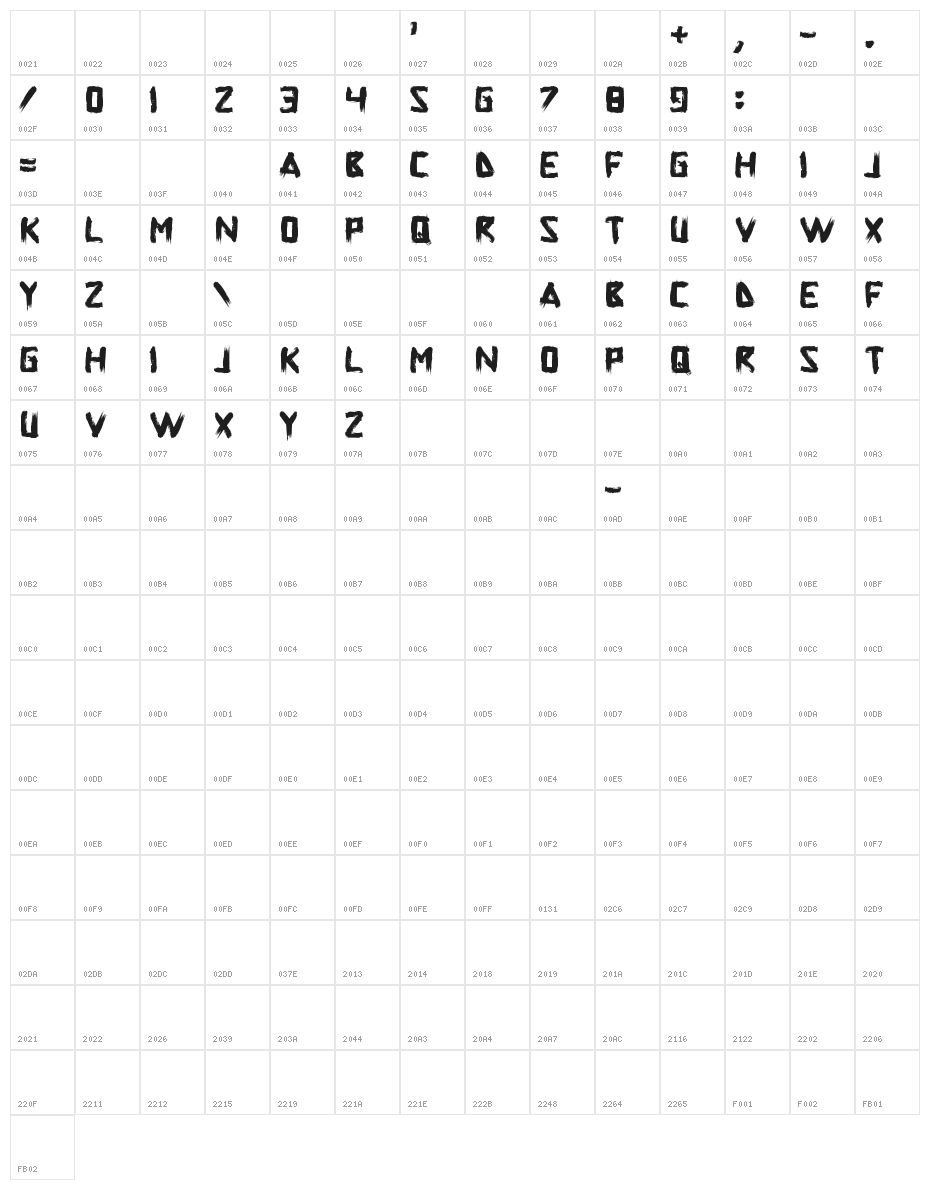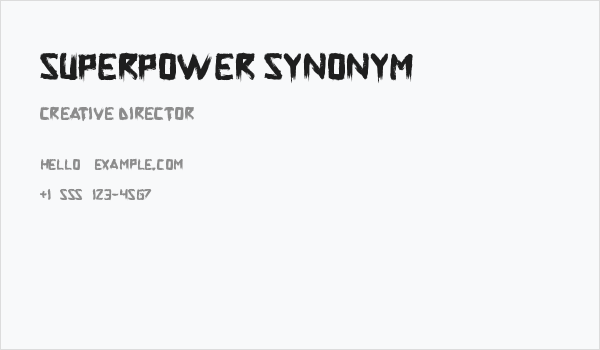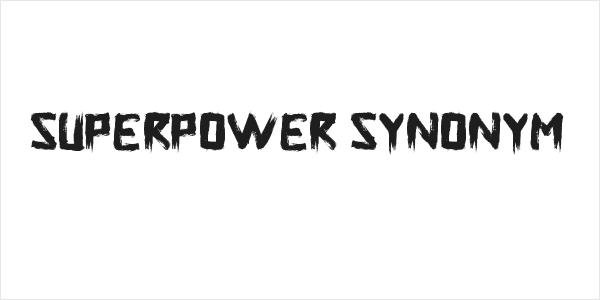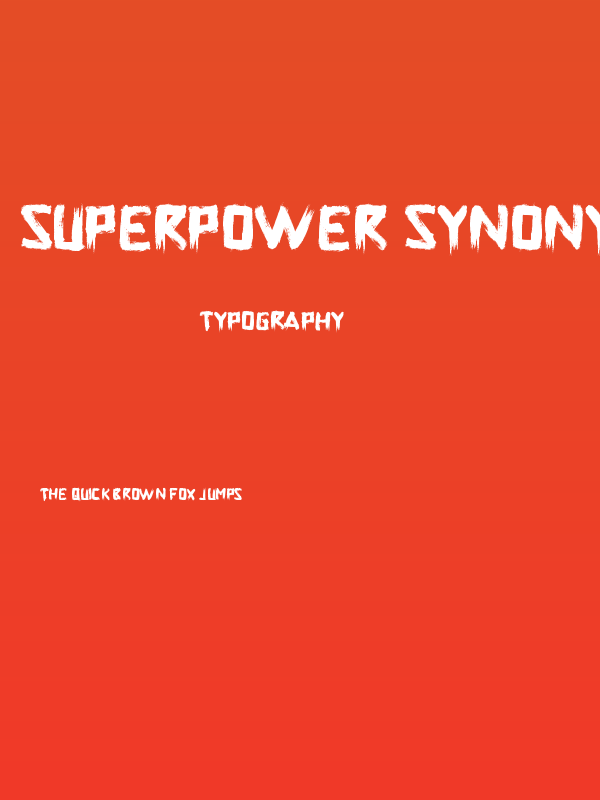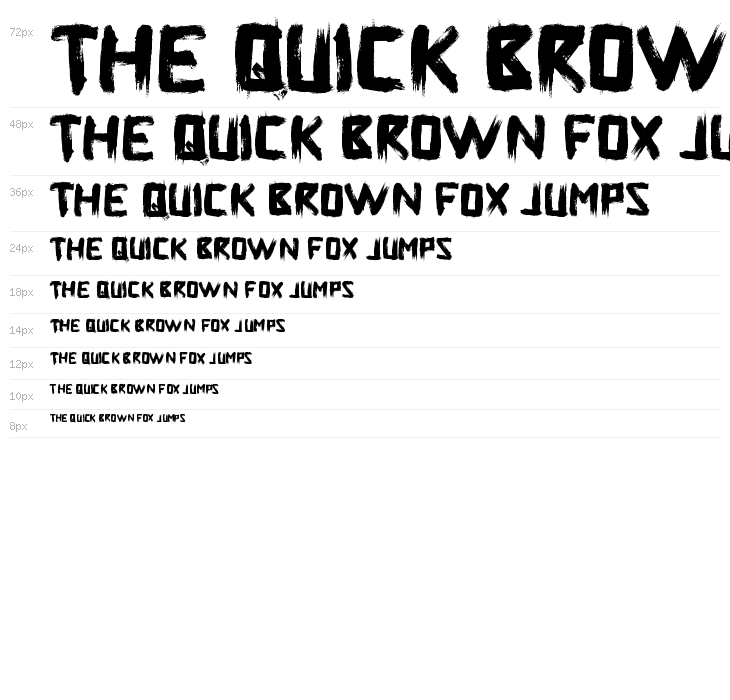
Superpower Synonym Font
✎ Calligraphic
| Stile generale | Modern, Artistic |
| Progetti proposti | Ideal for posters, album covers, graffiti art, and branding that requires a bold, artistic flair. |